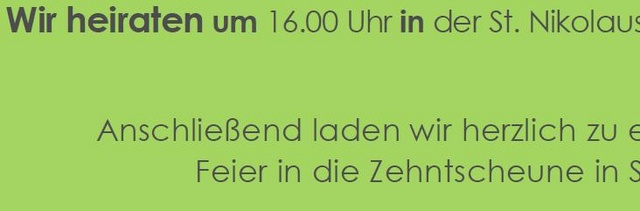
Welche Schrift ist das - oder welche ist ähnlich?
suche die Schrift (oder eine ähnliche) die im beigefügten Bild für den Text verwendet worden ist.
Jetzt werde ich übermütig und frage noch gleich nach einer weiteren Schrift:
Wenn deine Frage hiermit befriedigend beantwortet ist, würde ich diesen Strang mal kurz entführen ... :roll:
Die Gibson hast du hier in letzter Zeit, glaube ich, öfter mal empfohlen. Hast du die denn installiert und mal so ein bisschen erforscht? Taugt die als Arbeitstier?
Auf dem ersten Blick gefällt sie mir ganz gut und sie ist ja auch ›bezahlbar‹. Aber bevor ich sie mir auf blauen Dunst ohne dazugehörigem Projekt zulege, hätte ich gerne noch eine praktisch erfahrene Einschätzung :-)
Ich halte schon länger Ausschau nach einer geometrischen Grotesk bzw. Futura-Alternative, die auch im Fließtext angenehme Ergebnisse erzielt. Außerdem wären runde Punktierungen und zwei Schriftweiten schön. Die Gibson geht da schon in die gewünschte Richtung, trotzdem bin ich aufgrund der Condensed-Schnitte und Sprachunterstützung bisher immer wieder bei der Avenir (Next) gelandet. Deshalb kann ich Dir leider nur von dieser aus der Praxis berichten.
Die Gibson hat mir Kathrin heute in Erinnerung gerufen. Vielleicht weiß Sie oder jemand anderes etwas mehr zu sagen? :-?
:tuschel: Die Tatsache, dass sie ‚nur‘ vier Strichstärken, 371 Glyphen und keine Condensed-Schnitte aufweist, spricht (bei mir) allerdings mittlerweile nicht mehr für ein „Arbeitstier“. :roll: Trotzdem scheint es eine sehr angenehme Textschrift zu sein. :-)
Die Gibson hat mir Kathrin heute in Erinnerung gerufen. Vielleicht weiß Sie oder jemand anderes etwas mehr zu sagen? :-?
Die Avenir hatte ich letztes auch neu entdeckt, früher™ fand ich die nicht so toll :-?
Ich habe die Gibson zum ersten Mal gestern in dem Beitrag über Fontpiraterie gesehen, den Ralf hier im Forum eingestellt hat. Die Schrift hat mir in der Onscreen-Anwendung in der Dokumentation spontan sehr gefallen und deswegen habe ich im Abspann aufgepasst, ob der Schriftname genannt wird. Und tatsächlich, genannt wurde: Gibson. Verwendet habe ich die Schrift selber noch nie, da kann ich leider auch nicht weiterhelfen. :-)
So geometrisch finde ich die gar nicht, gerade wegen dem zweistöckigen a.
Und die Kursive finde ich interessant: diese leichten Einschwünge haben was.
Insgesamt ist sie auch etwas gothamesk, oder 8-)
Na ja, ich werde sie mal im Hinterkopf behalten ...
ebenfalls nicht zu verachten: neutraface. in den usa wohl etwas überstrapaziert, aber in europa sehe ich sie gar nicht so häufig. auch wenn es keine condensed-schnitte und nicht so viele strichstärken gibt, finde ich die kursive besonders schön. keine schrift, in der ich einen roman setzen würde, aber für kürzere längere texte finde ich sie tauglich.
Kollege CRudolph hat hier im Forum schon häufiger die Benton empfohlen – vielleicht ist die ja etwas für Lars?
Das hast Du glaube ich falsch in Erinnerung. Zumindest gearbeitet habe ich mit der Benton nämlich nicht. :roll:
Irgendwie mutiert das hier zum Empfehlung-falsch-abgespeichert-Thread :-P
Stimmt! Ich muss noch mal suchen, welche Schrift das war, die Christian empfohlen hatte – war auch eine schöne mit B, da bin ich mir ganz sicher!
Danke, dass Du noch einmal darauf eingehst! Die ist mir natürlich nicht entgangen und passt formal genau in das Fahndungsraster. ;-):-) Aber leider hat sie auch keine Condensed-Schnitte. Oder ist mir da etwas entgangen?
ebenfalls nicht zu verachten: neutraface. in den usa wohl etwas überstrapaziert, aber in europa sehe ich sie gar nicht so häufig. auch wenn es keine condensed-schnitte und nicht so viele strichstärken gibt, finde ich die kursive besonders schön. keine schrift, in der ich einen roman setzen würde, aber für kürzere längere texte finde ich sie tauglich.
Da hast Du Recht! Die ist ebenfalls nicht zu verachten. War bei uns sogar schon mal in der näheren Auswahl. Haben uns dann aber aufgrund der Weiten-Vielfalt und größeren x-Höhe für die Gotham entschieden (brauchten so eine für längere Ausstellungstexte).
Wenn Du die Wahl zwischen der Neutraface und Brandon Grotesk hättest, würdest Du Dich dann auch für die Neutraface entscheiden? Ich finde es schön, dass es dazu noch die passende Slab gibt. Auch sonst habe ich den Eindruck, dass man mir Ihr mehr anstellen kann. ;-):-P